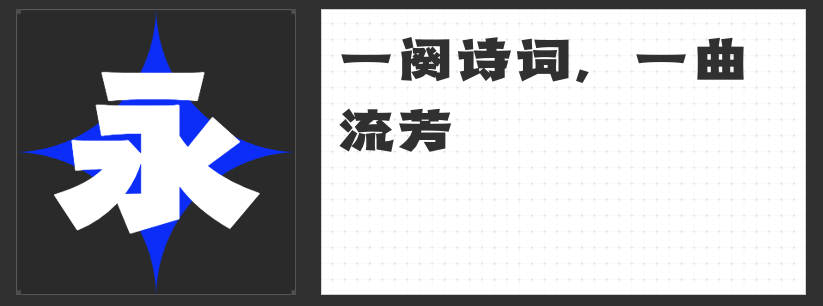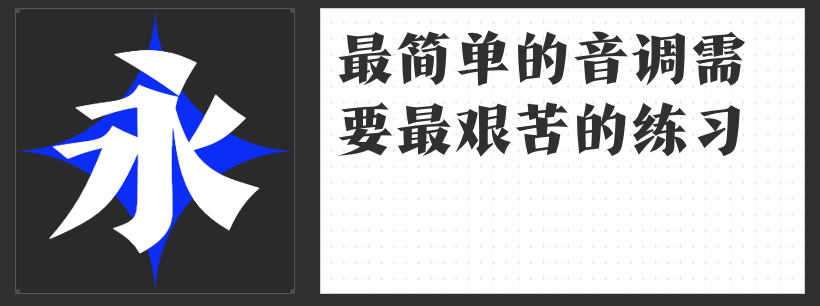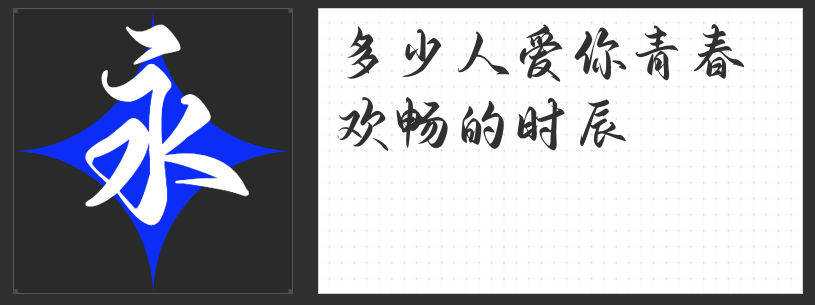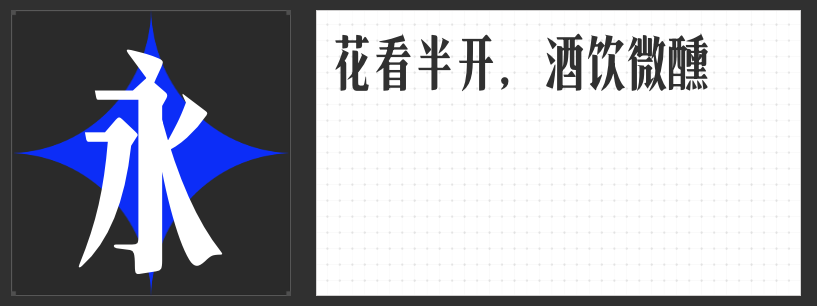
悬疑剧《孤舟》开播:适合影视的复古字体推荐
在民国题材的影视作品中,字体的选择往往能够巧妙地营造出那个时代的独特氛围,让观众瞬间穿越回那个风雨飘摇而又风华绝代的年代。今天,就为大家推荐四款专为民国题材量身定制的字体,它们各具特色,定能为您的影视作品增色不少。
1.造字侠热辣隶简
这款字体完美融合了传统与现代的元素,设计感强烈,视觉冲击力十足。其独特的隶书风格中融入了现代简约的设计理念,使得整体看起来既复古又不失时尚感。对于民国谍战类影视作品的海报设计而言,这款字体无疑能够迅速抓住观众眼球,营造出一种神秘而紧张的氛围。
2.也字工厂港风宋体
字体形状瘦长,线条流畅,透露出一种民国时期城市特有的韵味。无论是用于封面设计还是影片介绍,“也字工厂港风宋体”都能恰如其分地展现出那个时代的风貌。它的每一笔一划都仿佛在诉说着那个时代的故事,让人不由自主地沉浸其中。
3.高手字斋东京体
虽然名为“东京体”,但这款字体在民国题材的影视作品中同样有着广泛的应用空间。其独特的字形设计,使得它在海报类设计中能够脱颖而出,吸引观众的注意力。无论是复古风还是现代感,这款字体都能轻松驾驭,为影视作品增添一抹独特的色彩。
4.也字工厂惊鸿行楷
作为一款手写体,也字工厂惊鸿行楷既有楷书的规整之美,又不失行书的灵动与流畅。在抗战题材的影视作品中,这款字体能够很好地传达出那种激昂、热血的情感。它的每一笔都仿佛在诉说着英雄们的英勇事迹,让人感受到那个时代的热血与激情。
这四款字体各具特色,无论是从设计感、风格还是适用性上,都能满足民国题材影视作品的不同需求。选择适合的字体,让您的影视作品在字间流淌出浓郁的民国风情。